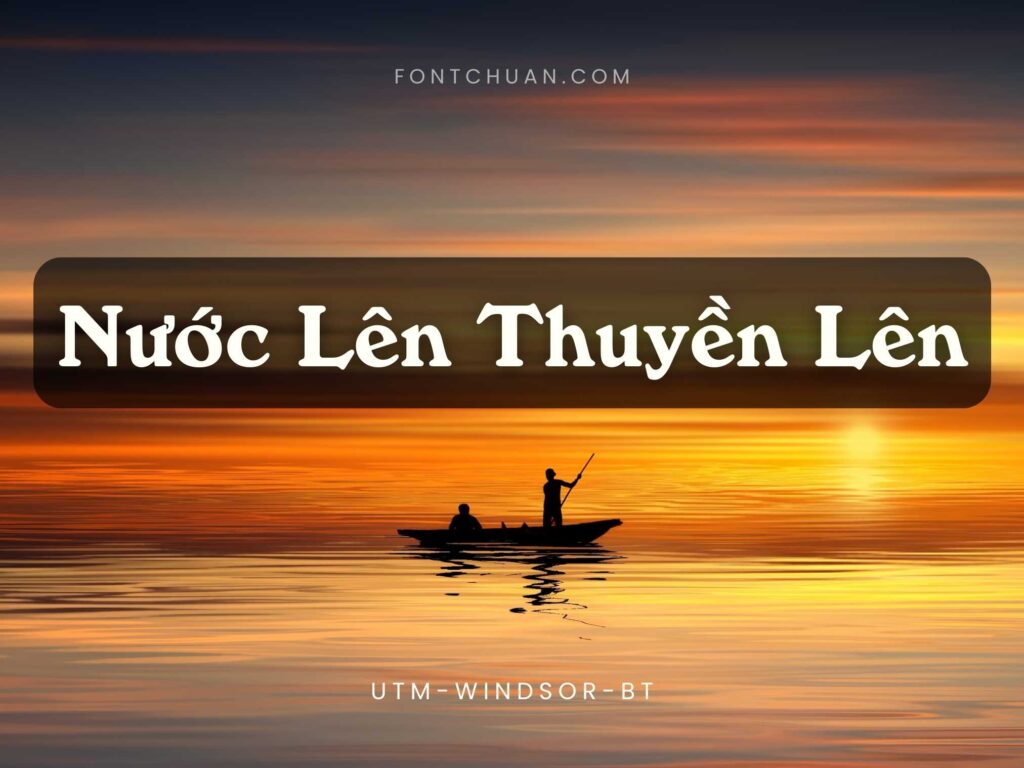
Windsor là một font chữ serif cổ điển, được thiết kế bởi Elisha Pechey vào năm 1905 và phát hành bởi xưởng đúc chữ Stephenson Blake. Font này mang phong cách thanh lịch với các đường nét uốn cong mềm mại, chân chữ rộng và tỷ lệ chữ có sự khác biệt độc đáo. Windsor đã trở thành một font được yêu thích trong các ấn phẩm mang phong cách cổ điển, tiêu đề in ấn và thiết kế đồ họa nghệ thuật. Kiểu dáng của font này tạo nên sự tinh tế, sang trọng và dễ nhận diện, khiến nó được ứng dụng rộng rãi trong lĩnh vực quảng cáo, xuất bản và thương hiệu.
Font này đã được Việt hóa bởi Thiên Minh, giúp hỗ trợ đầy đủ dấu và ký tự tiếng Việt, mang lại trải nghiệm trọn vẹn cho người dùng. Ngoài tiếng Việt, Windsor còn hỗ trợ nhiều ngôn ngữ khác, mở rộng phạm vi sử dụng trên toàn cầu. Thành viên của Font Chuẩn đã sưu tầm và giới thiệu Windsor đến cộng đồng thiết kế nhằm phục vụ nhu cầu đa dạng trong các dự án sáng tạo. Với sự kết hợp giữa cổ điển và hiện đại, Windsor phù hợp cho các thiết kế logo, tiêu đề, poster, thiệp cưới và các ấn phẩm quảng cáo mang tính nghệ thuật.